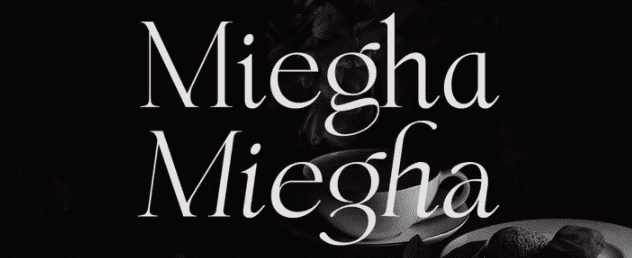
Miegha - шрифт с засечками, вдохновленный красотой классических засечек и каллиграфических стилей, как вертикальный, так и курсивный шрифт сочетается с современной привлекательностью и уникальным переплетом, высококонтрастный и легкий шрифт идеально подходит для женственных логотипов, модных голов и редакционных дизайнов, брендинговых проектов, Apparel Branding, упаковки, заголовков журналов, рекламы, футболок, открыток и многого другого.
- Альтернативы и лигатуры
- Цифры и пунктуация
- Символы с ударениями
- Поддержка нескольких языков